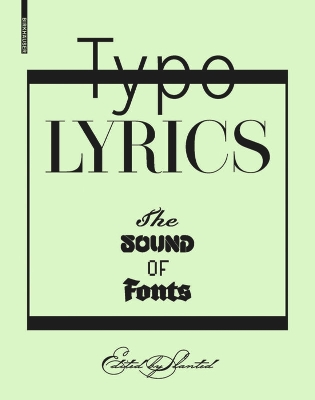
Grafikdesigner lieben Musik. Das zeigt nicht zuletzt die große Begeisterung der Leser des Typografie-Magazins Slanted" für die Rubrik Typo Lyrics" , in der Gestalter Musik mithilfe von Schrift ganz neu interpretieren. Für die gleichnamige Publikation haben sich renommierte Grafikdesigner wie Fons Hickmann sowie junge Talente aus der ganzen Welt von Songtexten zu innovativen Font-Designs inspirieren lassen. Entstanden ist eine Sammlung faszinierender Visuals Schriftbilder" , die zeitgenössische Fonts auf eine etwas andere Weise präsentieren. Das außergewöhnliche Zusammenspiel von Schriftgestaltung und Musik macht die Fonts lebendig und bringt sie regelrecht zum Tanzen. Im Gegensatz zu klassischen Musterbüchern oder Schriftenfächern wird so ein besonderer, emotionaler Zugang zur Typografie geschaffen, der das große Ausdruckspotenzial von Schriften deutlich macht. Analog zur traditionellen Schriftklassifikation gliedert sich das Buch in elf Kapitel, die sich jeweils mit einer Schriftfamilie und Songtexten einer bestimmten Musikrichtung auseinandersetzen.
The magazine Slanted, which is published and designed by MAGMA Brand Design in Karlsruhe, combines a focus on typography with other creative disciplines such as design, illustration, and photography. It has already been honored in numerous ways most recently with the red dot award communication design and recognition from the TDC, the ADC, ADC of Europe, and the European Design Awards. In 2 9, it also received the Designpreis der Bundesrepublik Deutschland (Design Award of the Federal Republic of Germany) silver award. In addition to the magazine, which is published four times a year, the blog www.slanted.de offers up-to-date news and information on typographic subjects.
Das Magazin Slanted" , herausgegeben und gestaltet von MAGMA Brand Design aus Karlsruhe, verbindet den Schwerpunkt Typografie mit anderen kreativen Disziplinen wie Design, Illustration oder Fotografie. Es wurde bereits vielfach ausgezeichnet zuletzt beim red dot award communication design, beim TDC, ADC, ADC of Europe oder den European Design Awards. Zudem erhielt es 2 9 den Designpreis der Bundesrepublik Deutschland in Silber vom Bundesministerium für Wirtschaft und Technologie. Parallel zum viermal im Jahr erscheinenden Magazin bietet das Weblog www.slanted.de aktuelle Informationen zu typografischen Themen.